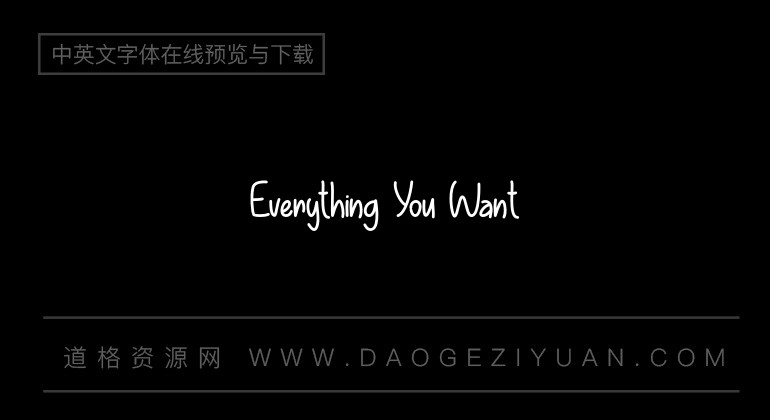
Everything You Want 是一款非常漂亮的手写风格字体,它的设计感十分的自然和舒适。这款字体的线条流畅,形似手写,字母之间的距离也比较适中,使得阅读体验非常愉悦。 Everything You Want 字体非常适合印刷和数字设计,特别是在卡片、海报、包装和招贴等应用场景中,可以营造出非常温馨和自然的感觉。它的颜色也非常容易搭配,可以和多种颜色进行搭配,从而达到更好的效果。 总之,如果你想要一款非常漂亮、自然的手写风格字体,那么 Everything You Want 可能是一个非常好的选择。内容介绍
Everything You Want是一款非常不错的手写艺术字体,具有很好的视觉感,适合于文化类的宣传设计、商业类品牌的广告和产品包装设计以及个性化文字排版等较多场景。